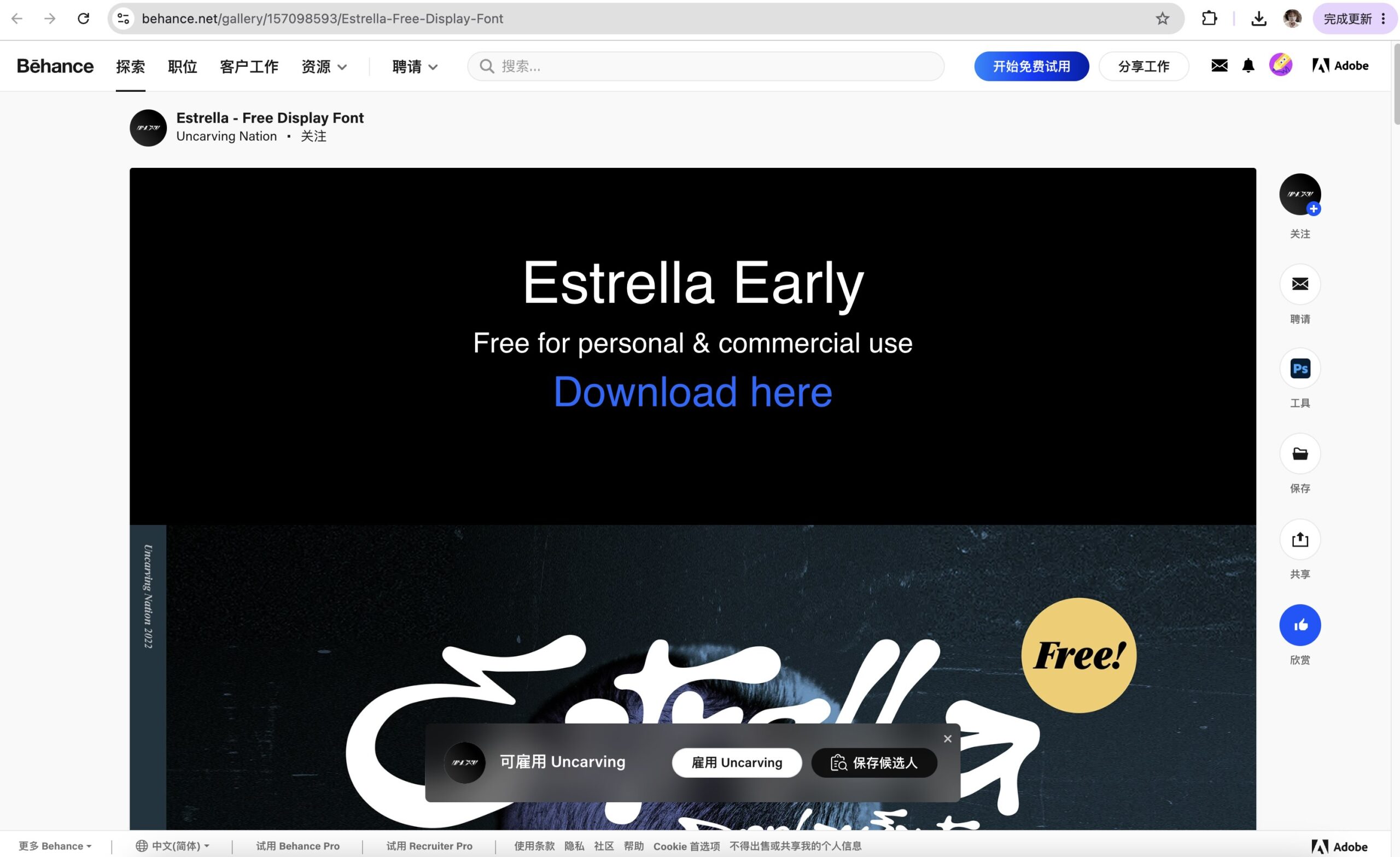
Estrella Early
Estrella Early 是一款由 uncarving 设计的现代手写风格英文展示字体,以自然书写轨迹为核心设计理念,将流畅的连笔结构、柔和的笔画变化与简洁的视觉比例相结合,打造出兼具艺术感与实用性的手写字体效果。
从整体字形来看,Estrella Early 采用较为自由的手写连笔形式,字母之间通过自然的连接关系形成连续的书写节奏。字体不像传统书法字体那样强调严格的笔锋变化,而是更接近现代设计中的快速手写效果,线条走势轻盈流畅,整体呈现出随性但经过设计控制的视觉状态。
字体最大的特点在于自然笔触与展示属性之间的结合。字母结构保留了手写过程中产生的起伏变化,例如起笔、转折以及收笔位置的细微变化,使字符拥有类似真实书写留下的动态感。同时,设计者对字母比例和连接关系进行了调整,使字体在放大使用时具备较强的视觉表现力,不会因为过度装饰而降低辨识度。
从细节观察,Estrella Early 的笔画粗细变化较为明显,部分笔画通过加粗处理增强视觉重量,而部分连接线则保持轻盈纤细,使整个字体形成鲜明的节奏对比。圆润的曲线与自然延伸的笔势,让字体具有现代手写标志常见的优雅感,适合用于需要传递个性与情绪的视觉设计。
在排版应用方面,该字体更偏向展示用途,适合短标题、品牌名称以及具有视觉焦点需求的设计场景。由于其独特的连笔结构和较强的艺术表现力,Estrella Early 能够很好地应用于品牌标识、产品包装、婚礼邀请函、社交媒体海报、音乐视觉以及时尚类设计项目。
总体来看,Estrella Early 是一款具有现代设计气质的手写连笔字体,通过流畅的笔画连接、自然的书写节奏以及精心调整的字形比例,将传统手写感与现代视觉设计结合在一起。
相比普通装饰型手写字体,Estrella Early 更强调文字作为视觉元素的表现力,在保持可读性的基础上增加了个性化特征。其轻盈、自由又富有艺术感的风格,非常适合应用于品牌设计、包装、海报以及需要营造独特氛围的创意项目。